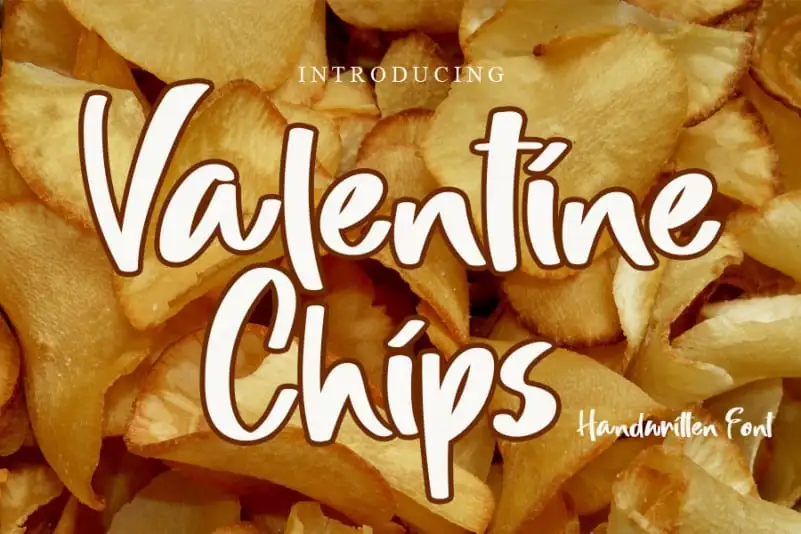
Valentine Chips Brush Font – Download Grátis
A Valentine Chips Brush Font é uma fonte de escrita cursiva encantadora e simpática, perfeita para quem busca algo diferente e divertido para seus projetos digitais. Esta letra, cheia de ondulações e um toque quirk, irá adicionar um toque de alegria e criatividade a cada design que você criar. Acredite quando digo que esta fonte vai transformar suas criações num encanto para os olhos. Avaliar esta fonte é como receber um convite para uma festa divertida, onde as pessoas se expressam com palavras escritas de forma espontânea e amorosa. Se você já experimentou outras tipografias, pode adorar a sensação única que a Valentine Chips Brush Font oferece. Ela é perfeita para criar cartões de aniversário românticos ou tags festivas enquanto traz um toque delicado e pessoal às suas criações digitais. Você vai amar o resultado final, garantido.